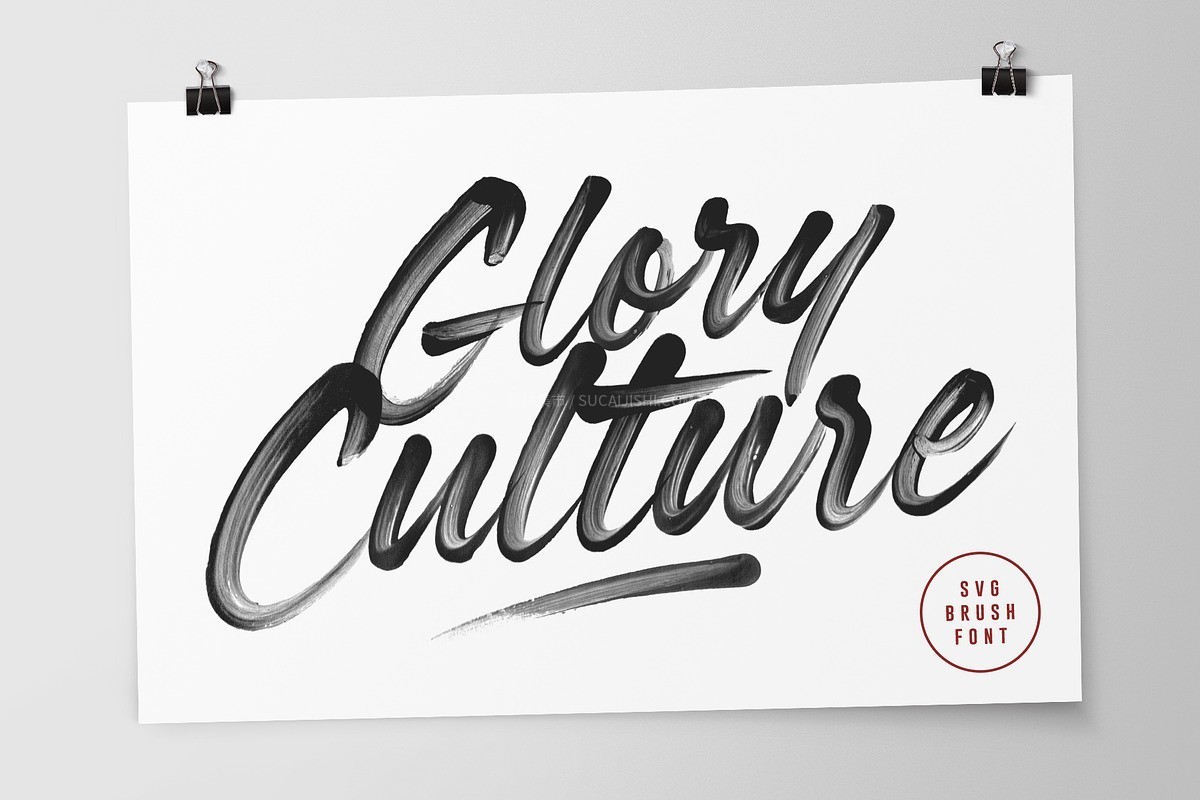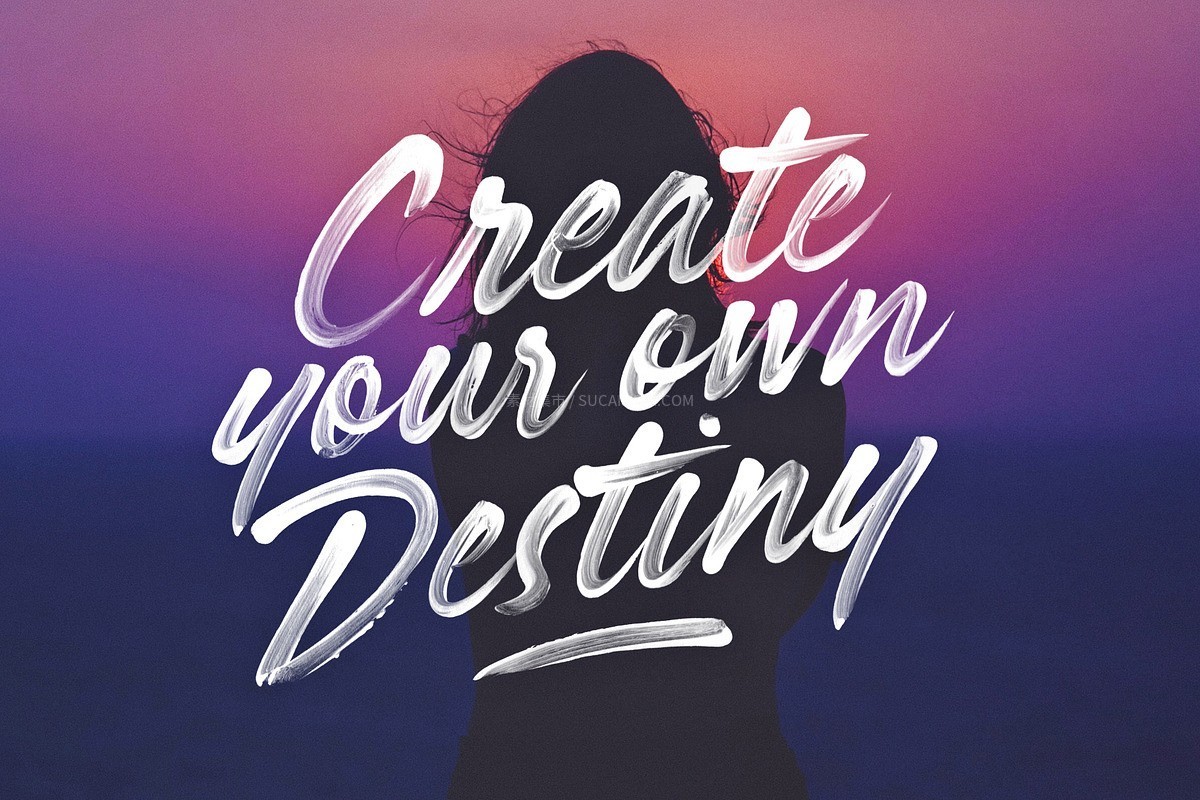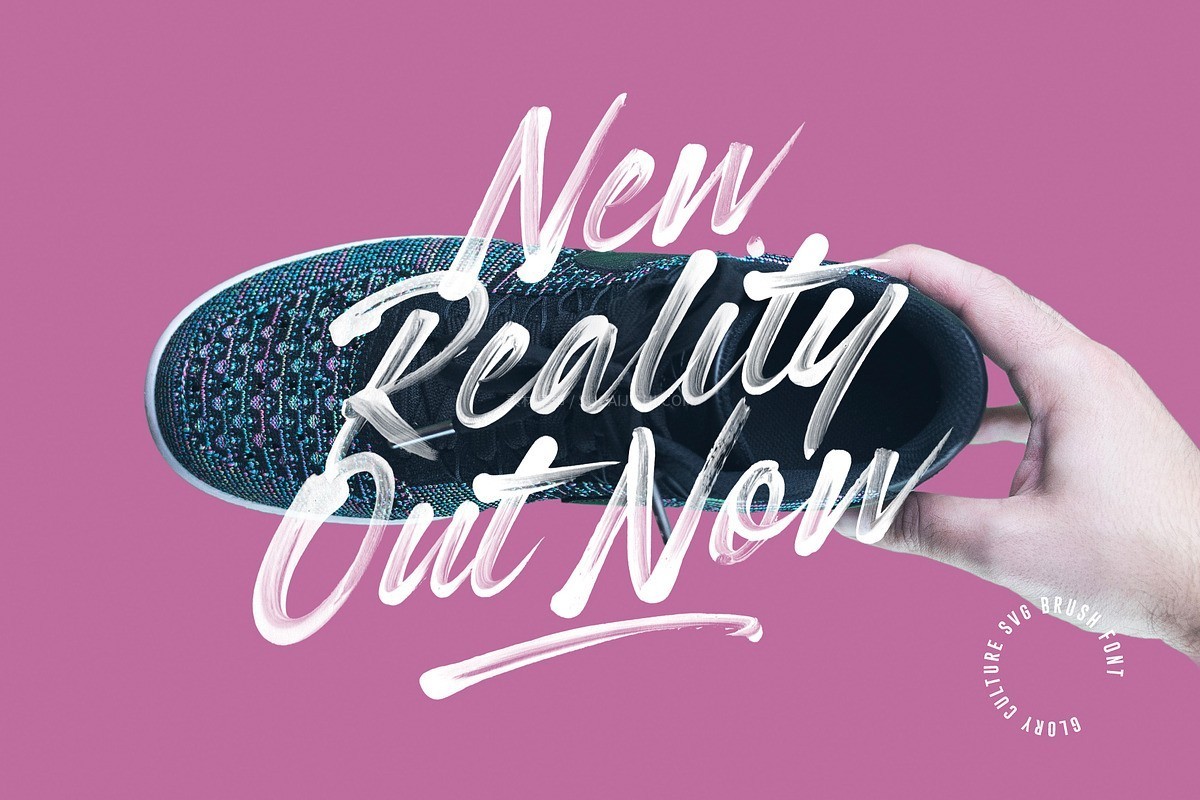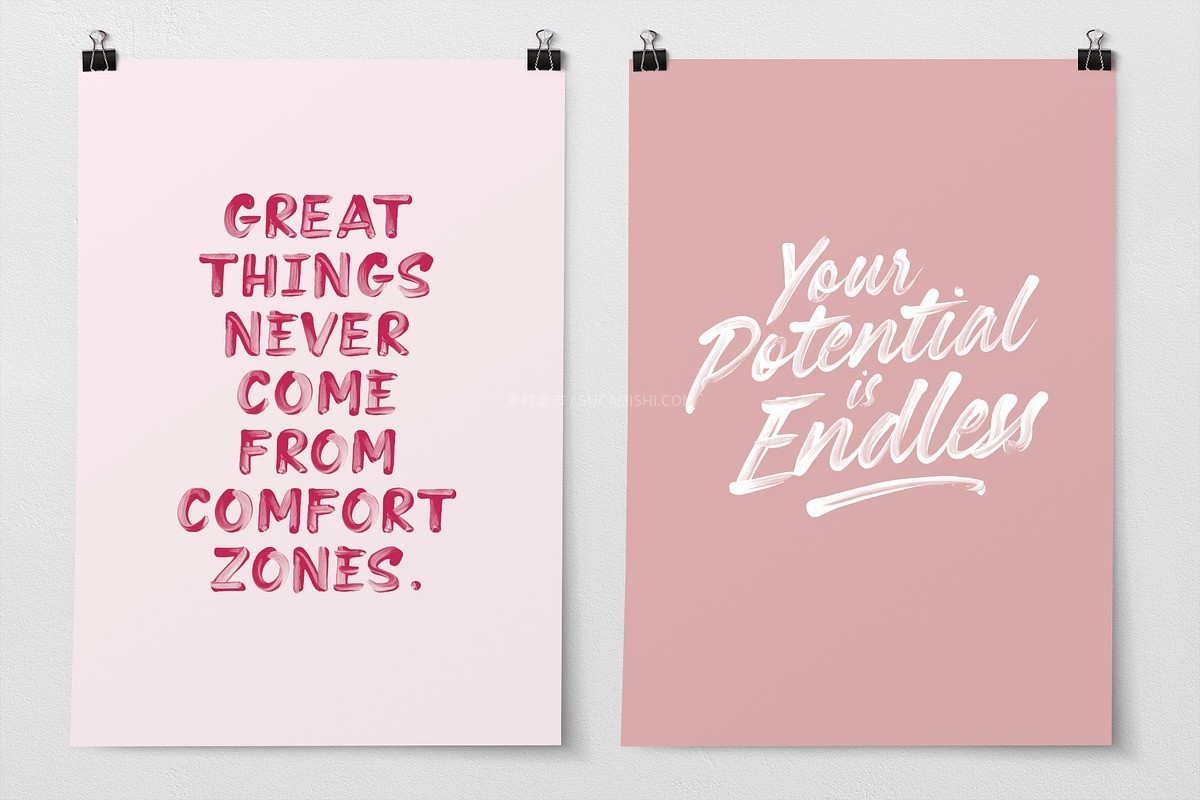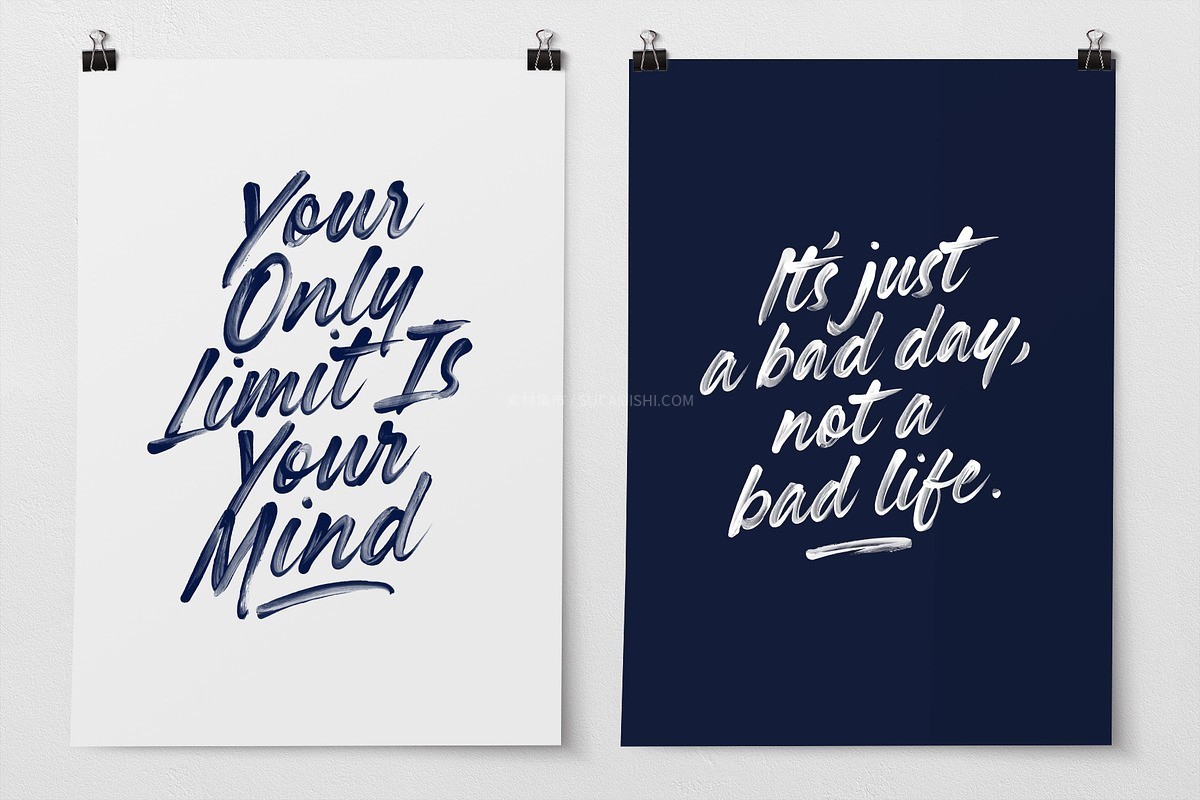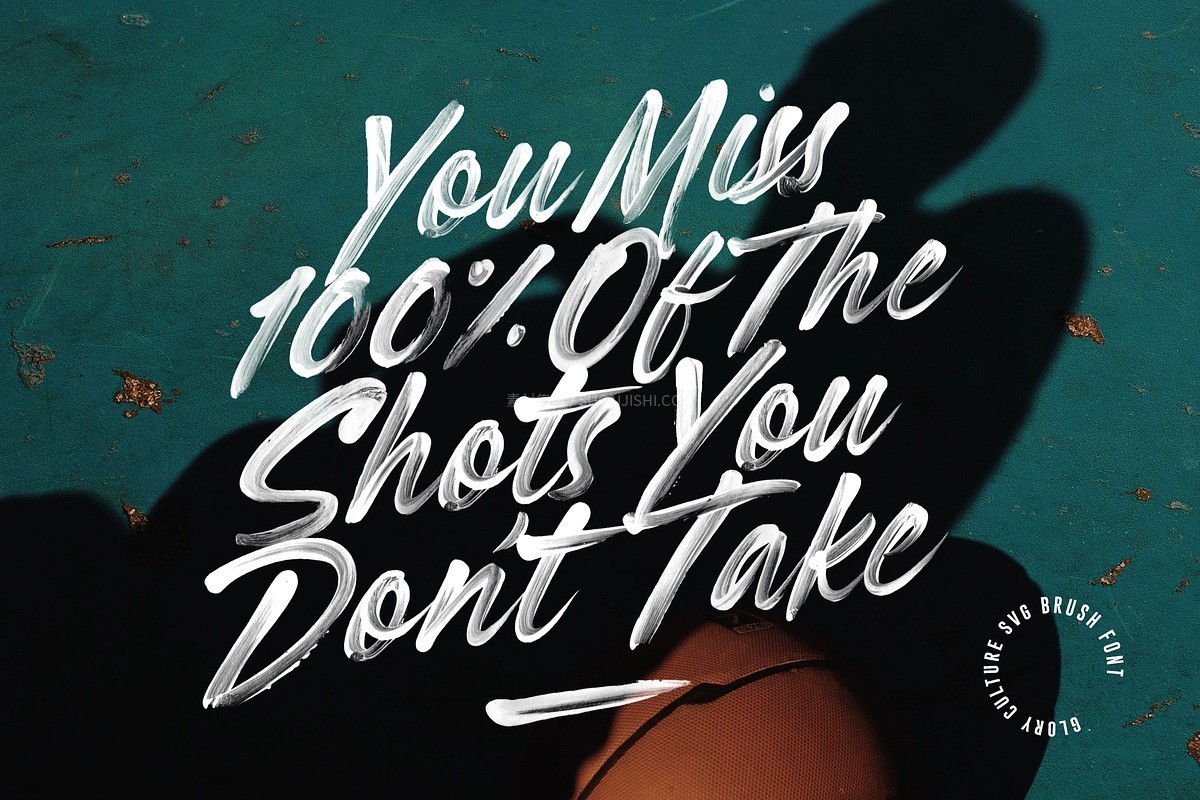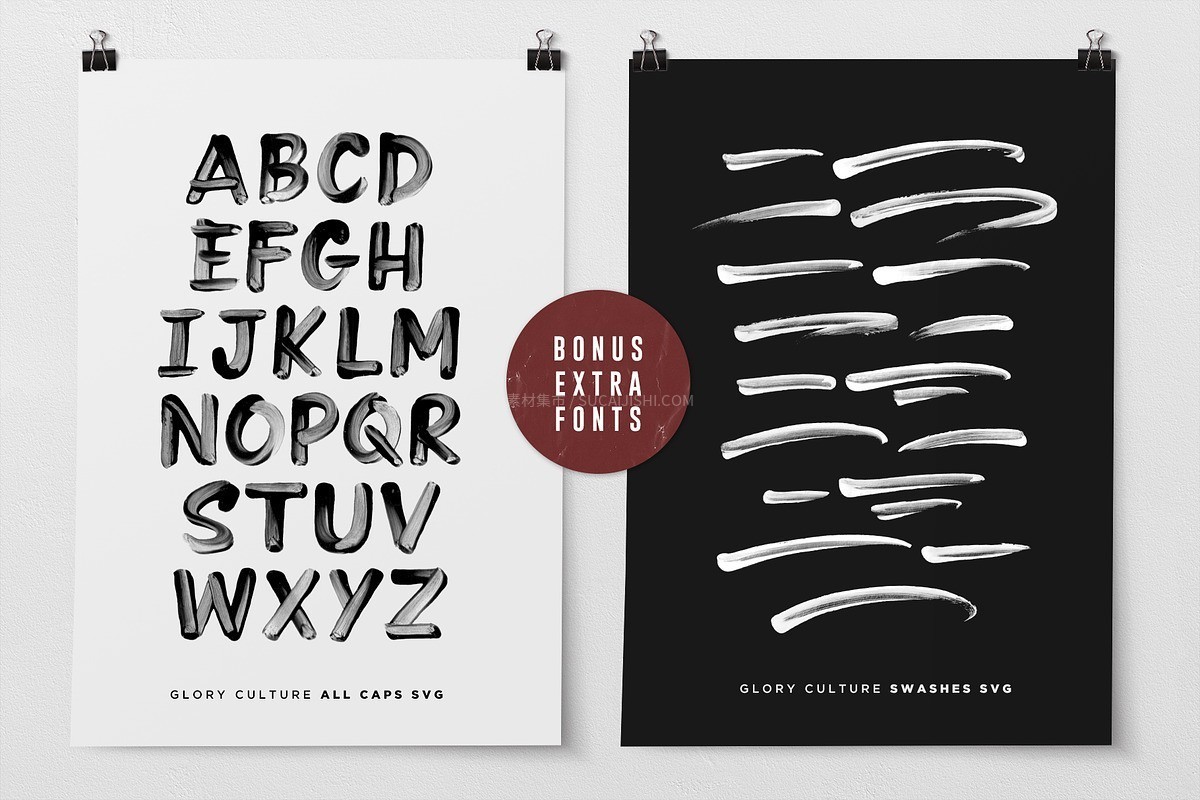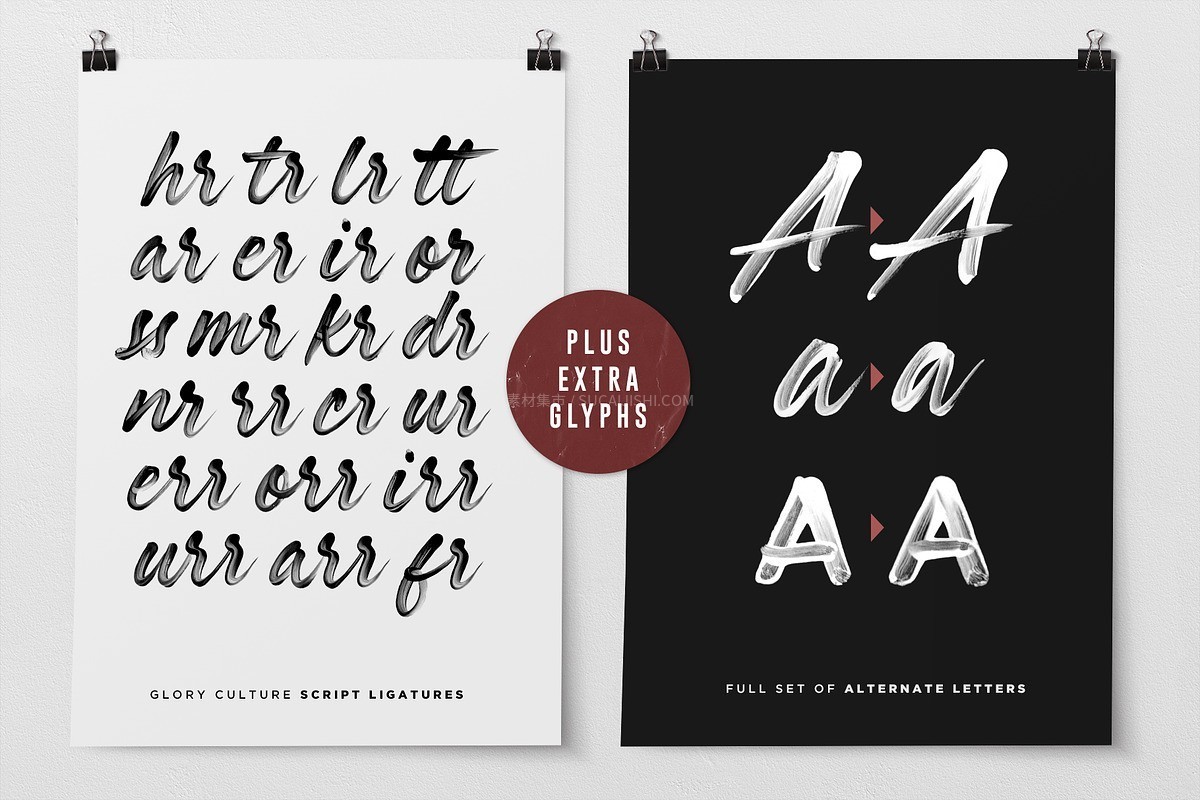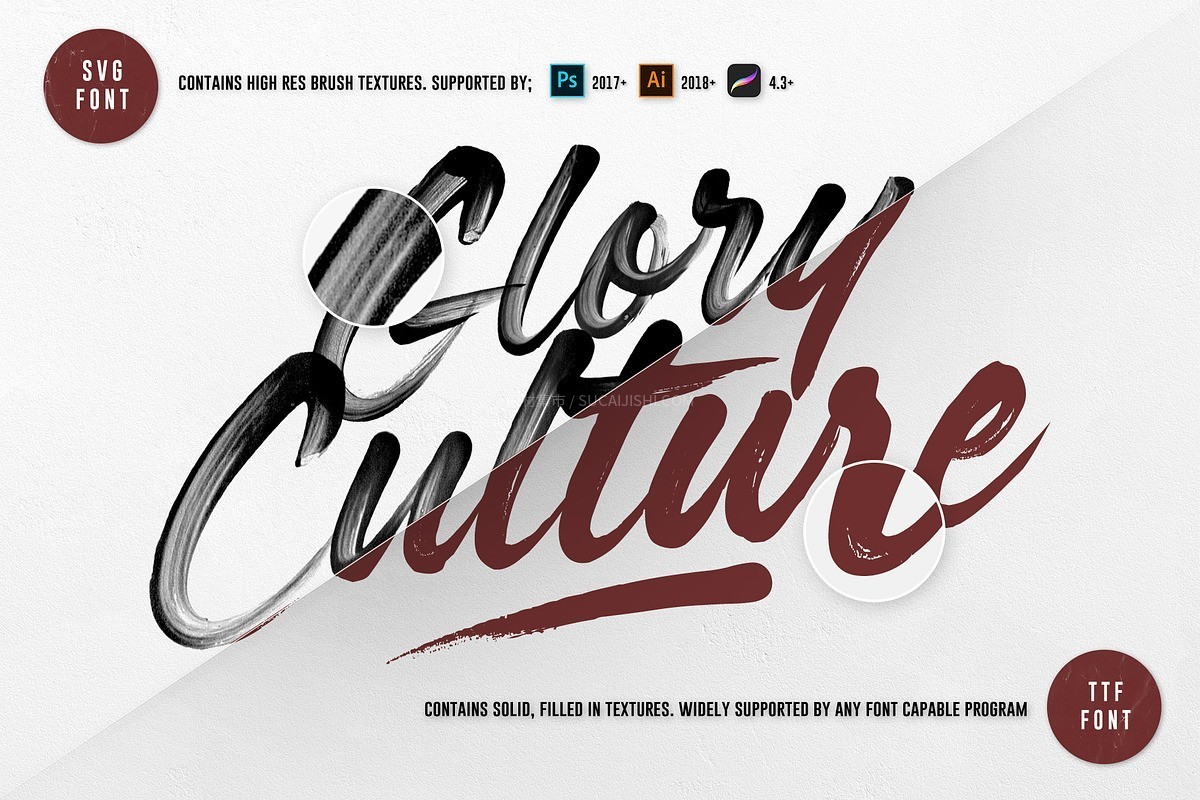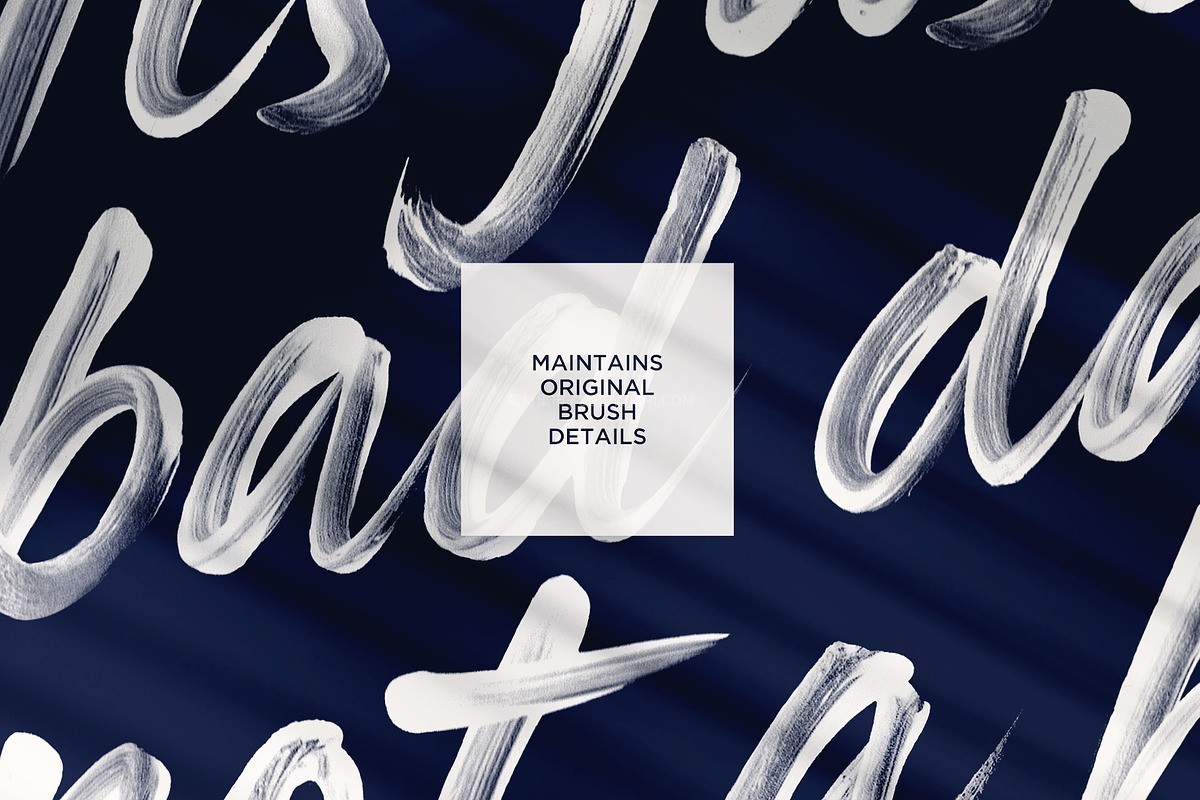
Glory Culture 现代手刷SVG字体
Glory Culture 是一款清新现代的 OpenType-SVG 笔刷字体。得益于先进的 SVG 字体技术,它完美保留了原始手绘笔触的丰富细节与透明纹理,只需轻松输入,即可呈现极具个性和真实感的视觉魔力!字体包内容丰富,包含高清晰度的常规版、提供更多布局选择的替换字母版(Alt)、效果更佳的全大写版,以及 18 款用于添加自定义效果的花式符号(Swash)。字体内置 27 种连字,让排版更加自然流畅。此外,还贴心提供了广泛支持的传统矢量化 TTF 格式版本(支持多种语言),满足您的不同设计需求。